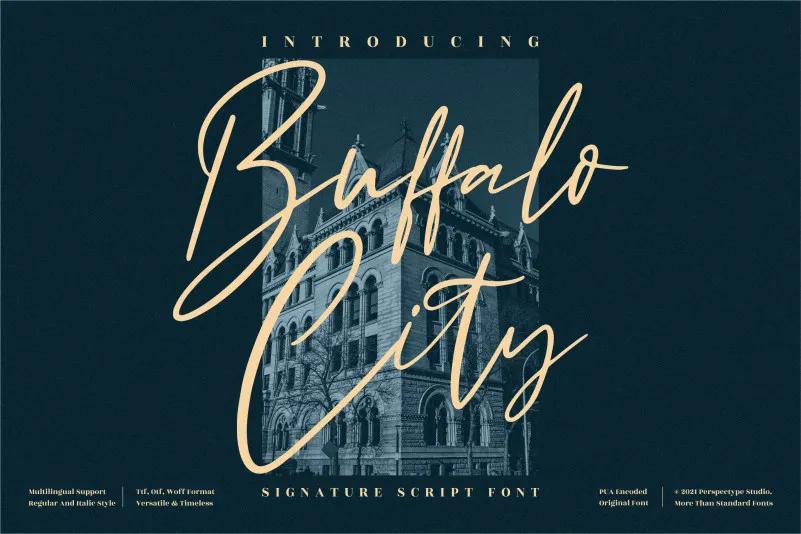
A Buffalo City Font é uma elegante fonte escrita à mão com traços finos, projetada para adicionar um toque sofisticado e singular a qualquer projeto. Como sua descrição original sugere, essa letra curiosa pode ser incorporada facilmente em trabalhos que buscam aquela sensação única e especial. Essa fonte é perfeita para aqueles que desejam dar um ar pessoal aos materiais digitais ou impressos, oferecendo um toque que destaca o trabalho com um olhar atencioso e moderno. Ideal para personalizar designs de revistas, gráficos publicitários, peças de arte digital, ou qualquer outro meio que exige uma textura delicada e única. Com sua proposta de criar um design atraente e individualista, essa fonte é perfeita para designers buscando dar um toque especial à suas criações.